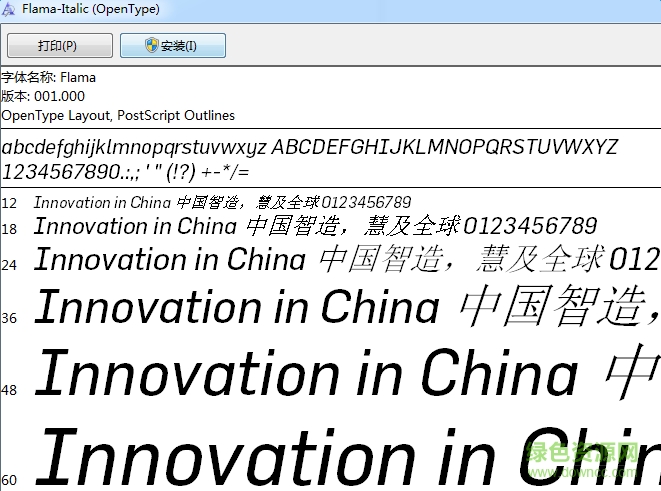
flama英文字體
flama字體是一款非常具有個(gè)性的英文字體,該字體可以廣泛應(yīng)用于報(bào)紙雜刊、學(xué)術(shù)論文、宣傳海報(bào)、ppt、影視制作以及任何使用文字的領(lǐng)域,有需要的朋友可以免費(fèi)下載收藏。
flama字體是一款英文字體庫中的個(gè)性字體,該字體擁有超瀟灑飄逸的風(fēng)格,讓用戶感受到一種賞心悅目的快感,有喜歡的朋友就趕快來綠色資源網(wǎng)下載使用吧!